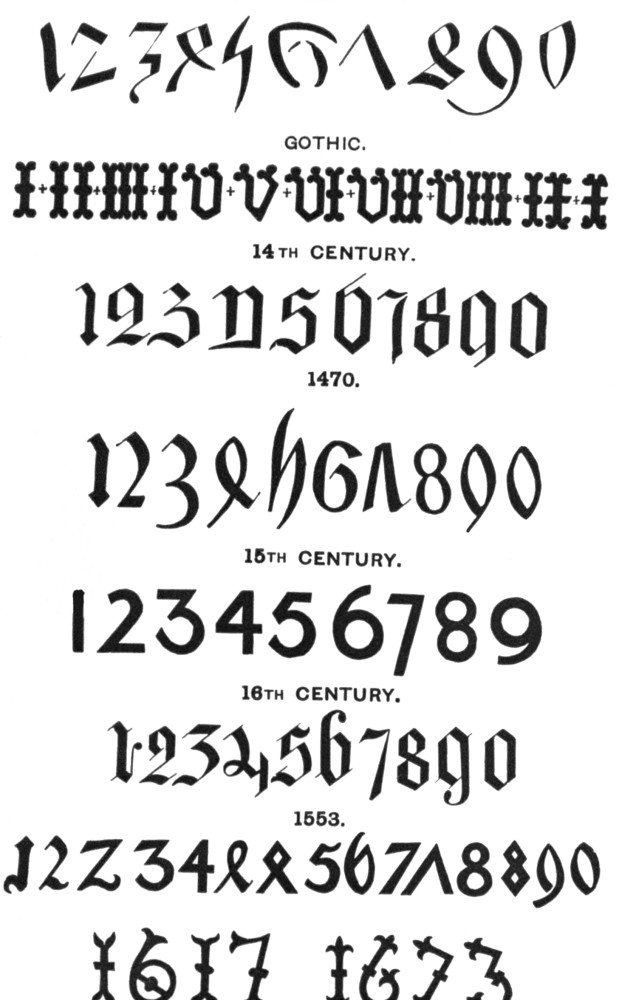
История немецкого языка
Он является официальным языком Германии, Австрии, Лихтенштейна, одним из официальных языков Швейцарии, Люксембурга и Бельгии. Немецкий язык относится к индоевропейской семье языков (германская ветвь). Письменность — на основе латинского алфавита.До начала XX в. официально использовался готический шрифт (в частности, существовал особый готический рукописный шрифт). Буквы в общепринятом европейском начертании используются сначала неофициально с XIX в., а после победы Ноябрьской революции 1918 г. вводятся официально. Попытки нацистов вернуть готический шрифт в качестве официального успеха не имели, и в настоящее время он используется лишь в декоративных целях.
Но как лучше всего изобразить Боуи в совершенно новой и мгновенно знакомой манере? Одним из ответов был цвет: весь вид шоу будет залит оранжевым — оранжевый цвет волос Зигги Стардаста, оранжевый цвет Low . Еще одно решение — это шрифт для вывесок, необходимых, чтобы направлять посетителей по выставке и украсить рекламные плакаты и товары.Здесь выбор был менее очевиден. Первоначальные мысли обратились к обложкам прошлых альбомов (Барнбрук работал с Боуи над дизайном обложек для своих пластинок с 2002 года). Возможно, коренастый шрифт ITC Zipper, напоминающий Hunky Dory , или блестящая надпись Cristal 1950-х годов Aladdin Sane ? Но это зафиксировало бы взгляд на определенном звуке и времени.